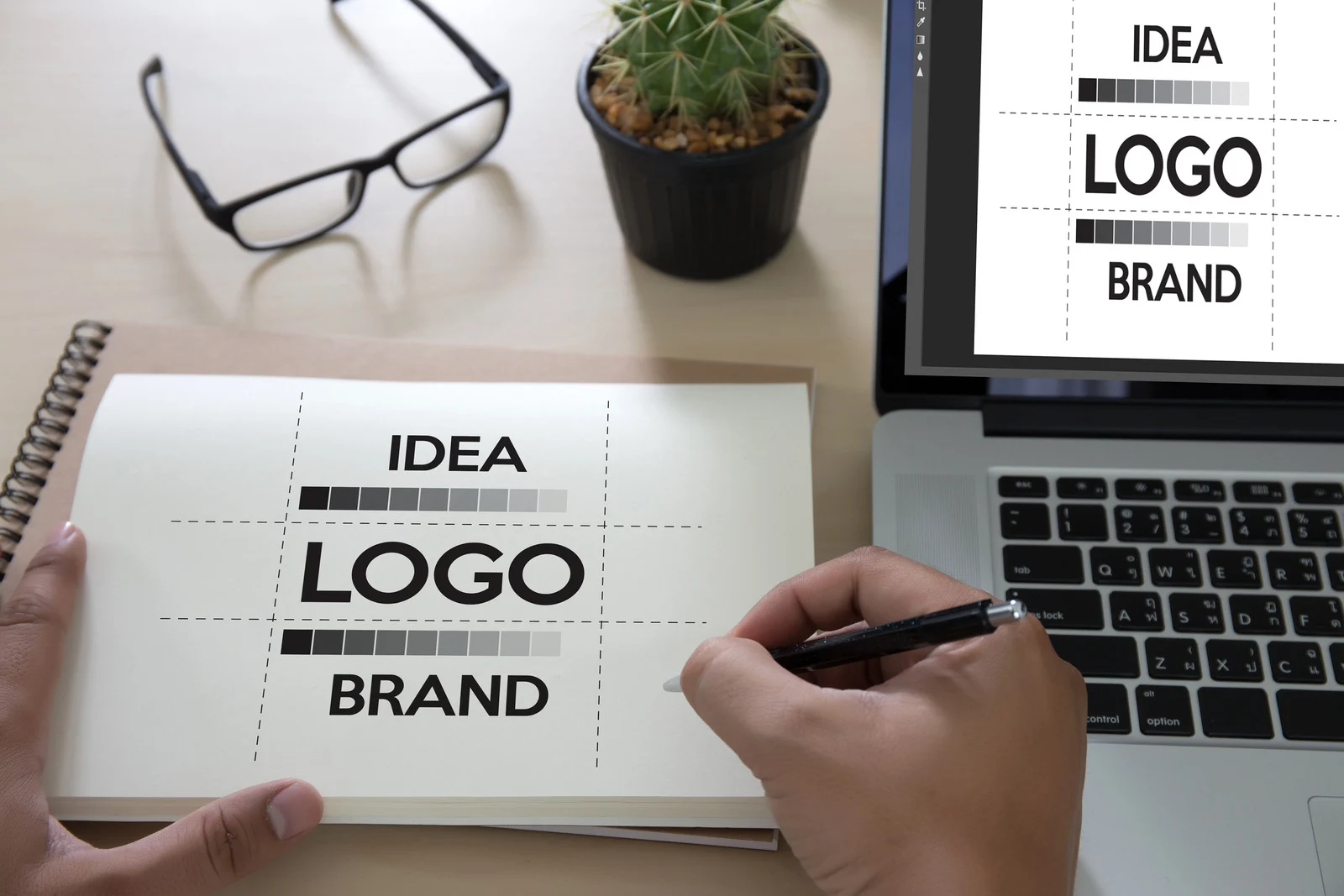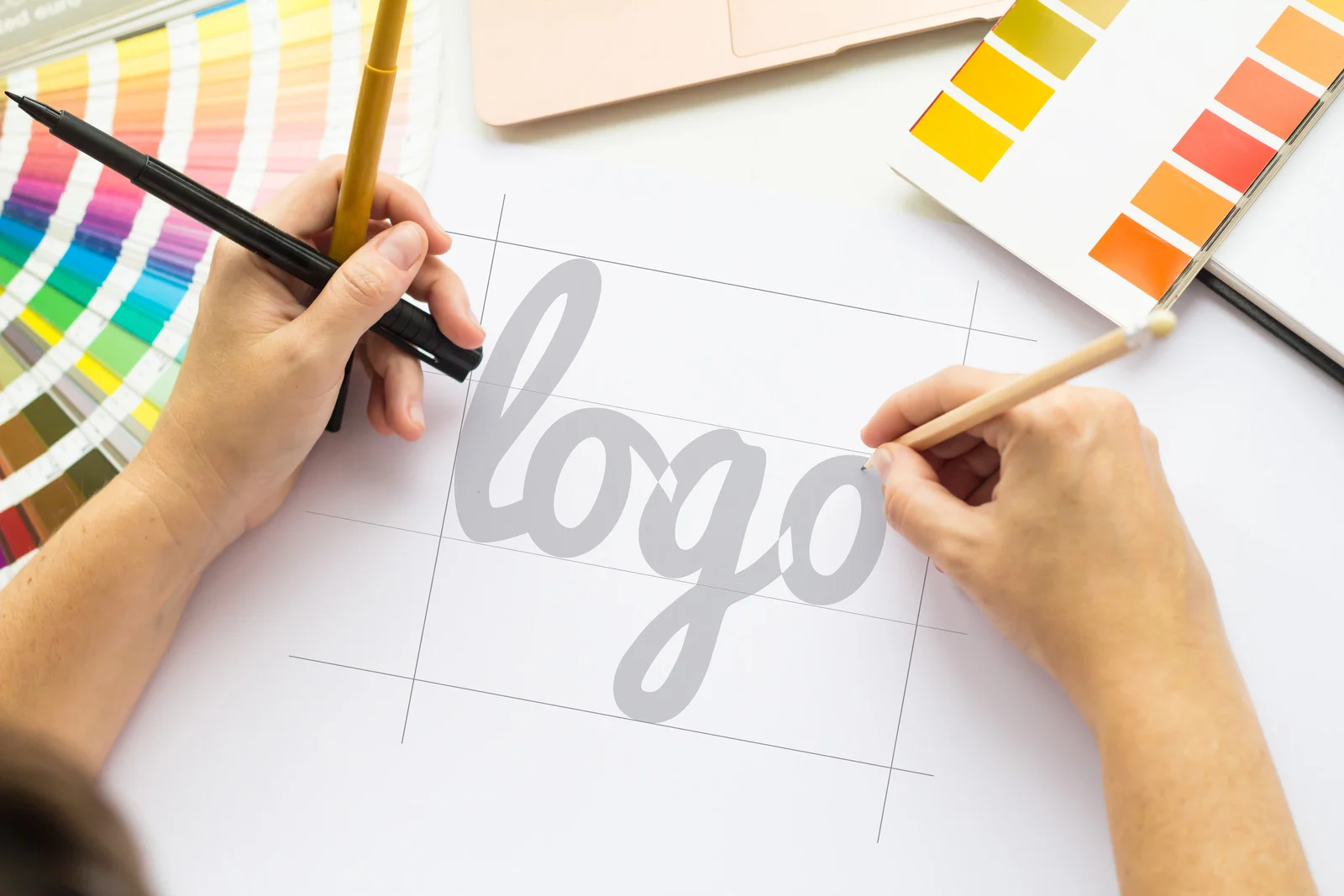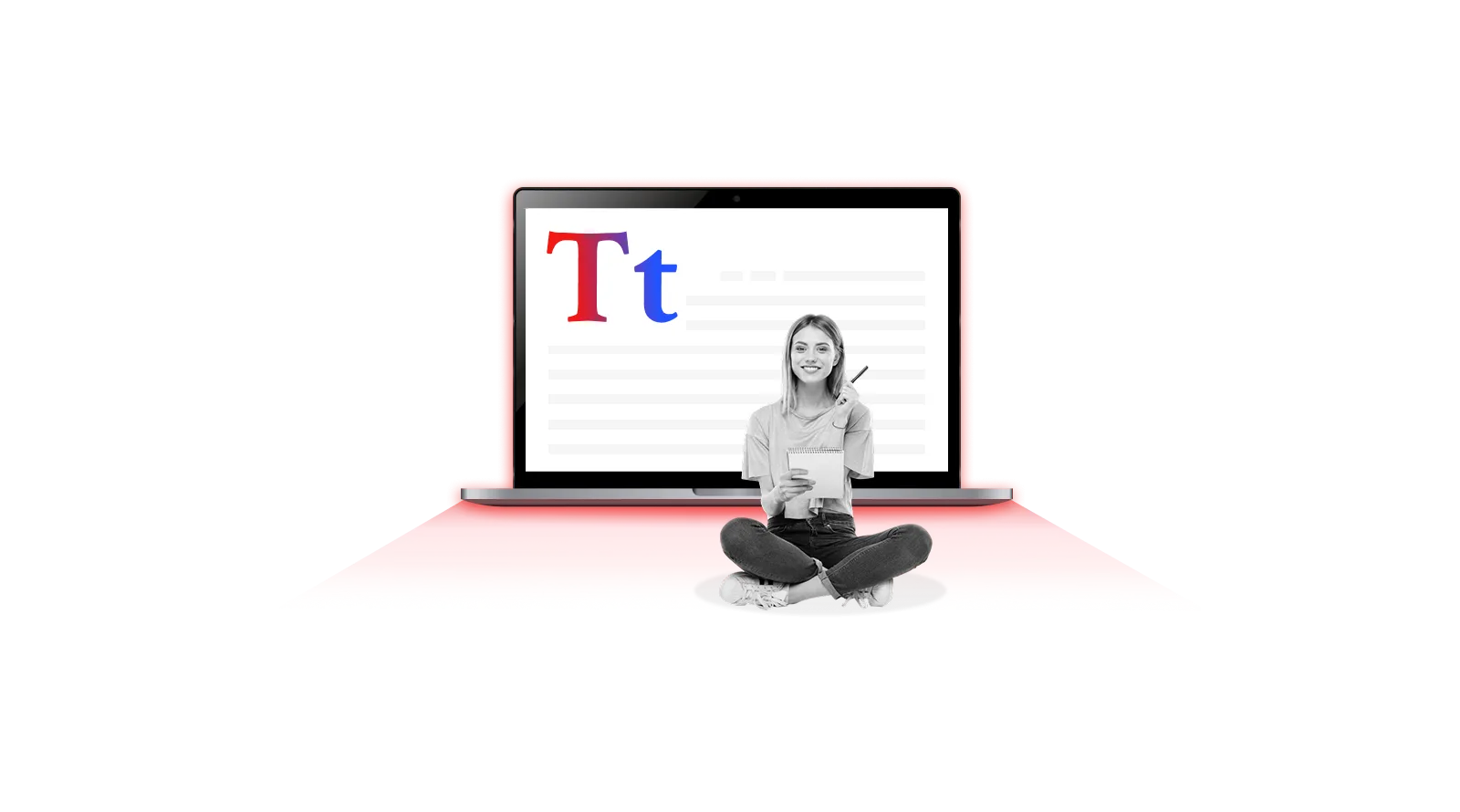
จิตวิทยาการเลือกฟอนต์ สร้าง Brand Awareness ให้ตรงใจแบรนด์และลูกค้าจดจำ
คุณเคยสงสัยไหม ทำไมเห็นโลโก้แบรนด์หรูแล้วรู้สึก “แพง” หรือเห็นป้ายร้านกาแฟบางร้านแล้วรู้สึก “อบอุ่นเป็นกันเอง” ทั้งที่ยังไม่เคยเดินเข้าไปใช้บริการ
คำตอบนั้นซ่อนอยู่ในพลังของ “ตัวอักษร” หรือ “Font” หลายคนอาจมองว่าฟอนต์เป็นเพียงเรื่องของความสวยงาม แต่ในทางการตลาดและจิตวิทยานั้น ฟอนต์ เปรียบเสมือนกับ “น้ำเสียง” ของแบรนด์ หน้าที่ของฟอนต์ คือการสื่ออารมณ์ บุคลิก และสร้างความน่าเชื่อถือ โดยไม่จำเป็นต้องเอ่ยคำพูดใด ๆ
การเลือกใช้ฟอนต์ที่ใช่จึงเป็นกุญแจสำคัญ ที่จะช่วยสร้าง Brand Awareness ให้แบรนด์ของคุณได้เข้าไปนั่งอยู่ในใจของลูกค้าตั้งแต่แรกเห็น
ทำไมความหมายของฟอนต์ ถึงมีผลต่อจิตวิทยาและ Brand Awareness?
คุณเคยไหม ที่สามารถจดจำแบรนด์ Disney หรือ Coca-Cola ได้จากการมองเห็นโลโก้เพียงแวบเดียว คุณอาจไม่เคยสังเกตว่าในโลโก้นั้นได้แฝงสิ่งที่ทรงพลังยิ่งกว่า และฝังตัวอยู่ในทุกส่วนของการสื่อสารแบรนด์นั่นก็คือ “ฟอนต์” ซึ่งมีผลโดยตรงต่อความรู้สึกและการรับรู้ของมนุษย์ ในระดับจิตวิทยา ฟอนต์ ไม่ใช่แค่ภาพลักษณ์ แต่ยังเป็นตัวกระตุ้นอารมณ์และความจำ ที่มีผลต่อการตัดสินใจของผู้บริโภคอย่างคาดไม่ถึง
การเลือกใช้ ฟอนต์ จึงส่งผลโดยตรงต่อ Brand Awareness ผ่านกระบวนการทางจิตวิทยาดังนี้
สมองจดจำ “รูปทรง” ก่อน “ความหมาย”
ก่อนที่เราจะอ่านออกว่าข้อความเขียนว่าอะไร สมองจะบันทึก “รูปร่างของตัวอักษร” (Visual Shape) ไปก่อนแล้ว หากคุณใช้ฟอนต์ที่มีเอกลักษณ์และสม่ำเสมอ สมองลูกค้าจะจดจำ “Pattern” นั้น และเชื่อมโยงกลับมาที่แบรนด์ของคุณทันที โดยที่ลูกค้าไม่ต้องย้อนกลับไปดูชื่อแบรนด์อีกครั้ง
สร้าง “อารมณ์ร่วม” ระดับจิตใต้สำนึกผ่านรูปทรง
Font แต่ละแบบมี “บุคลิก” ที่กระตุ้นความรู้สึกของมนุษย์ได้ต่างกัน เช่น
- เส้นโค้งมน : สื่อถึงความสุข ความเป็นมิตร (เช่น โลโก้ Disney)
- เส้นเหลี่ยมหนา : สื่อถึงความมั่นคง พลังอำนาจ (เช่น โลโก้ธนาคาร)
เมื่อลูกค้าเห็นฟอนต์ที่ตรงกับจริตของพวกเขา จะเกิดความรู้สึก “ไว้ใจ” และ “คุ้นเคย” ซึ่งเป็นรากฐานสำคัญของการตัดสินใจซื้อ
สร้างความแตกต่าง (Differentiation) ในเสี้ยววินาที
ในตลาดที่มีคู่แข่งมากมาย Typography (ศิลปะการจัดวางตัวอักษร) คือเครื่องมือที่ช่วยแยกแยะแบรนด์ของคุณออกจากคู่แข่งได้ชัดเจนที่สุด เพื่อให้ลูกค้าสามารถจดจำและแยกแยะแบรนด์ของเราได้ทันที เพียงแค่กวาดตามองในเสี้ยววินาที
4 กลุ่มฟอนต์ยอดนิยมและความลับที่ซ่อนอยู่ในลายเส้น
ในโลกการออกแบบแบรนด์ ฟอนต์ไม่ได้ต่างกันแค่ “รูปทรง” แต่ยังคงซ่อนความหมายทางจิตวิทยาที่สามารถเปลี่ยนภาพลักษณ์ของแบรนด์ได้อย่างคาดไม่ถึง
โดยทั่วไป ฟอนต์ถูกแบ่งออกเป็น 4 กลุ่มหลักยอดนิยม ได้แก่
Serif (ฟอนต์แบบมีเชิง)
เป็นฟอนต์ที่มีความทางการ ให้ความรู้สึกน่าเชื่อถือ, น่าเคารพ, หรูหรา โดยมีจุดเด่นคือ มี “เชิง ” หรือส่วนปลายเล็กๆยื่นออกมาจากตัวอักษร ทำให้อ่านง่ายและให้ความรู้สึกมั่นคง
เหมาะกับธุรกิจ : กฎหมาย, การเงิน, สถาบันการศึกษา, และแบรนด์แฟชั่น Hi-End
ตัวอย่างแบรนด์ที่ใช้ฟอนต์แบบ Serif : Rolex, Vogue, Dior
Sans Serif (ฟอนต์แบบไม่มีเชิง)
เป็นฟอนต์ที่ให้ความรู้สึกเรียบง่าย, ทันสมัย, เข้าถึงง่าย โดยมีจุดเด่นคือไม่มี “เชิง” ไม่มีส่วนตกแต่งมีเพียงลายเส้นตัวอักษรเรียบๆ
เหมาะกับธุรกิจ : Tech Startup, เว็บไซต์ E-Commerce, แอปพลิเคชัน, และแบรนด์ไลฟ์สไตล์คนรุ่นใหม่
ตัวอย่างแบรนด์ที่ใช้ฟอนต์แบบ Sans Serif : Facebook, Airbnb, Microsoft
Script (ฟอนต์ลายมือ/ตัวเขียน)
เป็นฟอนต์ที่เน้นความพริ้วไหว สื่อถึง “อารมณ์” ให้ความรู้สึก สง่างาม, โรแมนติก, สนุกสนานขี้เล่น จุดเด่นคือการเลียนแบบลายมือการเขียนด้วยปากกาหรือพู่กัน
เหมาะกับธุรกิจ : อาหารและเครื่องดื่ม, ความสวยความงาม, งานแต่งงาน, และสินค้าสำหรับเด็ก
ตัวอย่างแบรนด์ที่ใช้ฟอนต์แบบ Script : Coca-Cola, Cartier, Champion
Display/Modern (ฟอนต์พาดหัว/เฉพาะทาง)
เป็นฟอนต์ที่ถูกออกแบบมาเพื่อ “โชว์” หรือ “ดึงดูดสายตา” มักมีรูปทรงโดดเด่น แปลกตา สร้างความประทับใจตั้งแต่แรกเห็น
เหมาะกับธุรกิจ : โลโก้สินค้า, โปสเตอร์ภาพยนตร์, ธุรกิจบันเทิง, หรือแคมเปญโฆษณาที่ต้องการความโดดเด่น
ตัวอย่างแบรนด์ที่ใช้ฟอนต์แบบ Display : Disney, LEGO, Fanta
4 ขั้นตอนเลือก Font ให้ตรงใจแบรนด์ (Brand Personality Matching)
การเลือกฟอนต์ไม่ได้เป็นเพียงเรื่องของความสวยงาม แต่ฟอนต์คือ “น้ำเสียง” ที่แบรนด์ใช้สื่อสารกับลูกค้า ฟอนต์แต่ละแบบมีจิตวิทยาที่ซ่อนอยู่ต่างกัน การเลือกฟอนต์ที่ไม่เหมาะสมกับประเภทธุรกิจอาจเป็นการทำลายความน่าเชื่อถือของแบรนด์ แต่หากเลือกถูกต้อง ก็จะช่วยส่งเสริม Brand Awareness ให้ลูกค้าจดจำแบรนด์ของคุณได้ตั้งแต่แรกเห็น
โดย 4 ขั้นตอนการเลือก Font ให้ตรงใจแบรนด์ มีแนวทางดังนี้
กำหนดบุคลิกแบรนด์ให้ชัด (Brand Persona)
การกำหนดบุคลิกให้ชัดเจนเป็นการตอบคำถามว่า “แบรนด์ของคุณจะเป็นคนแบบไหน?” ก่อนที่จะเลือกฟอนต์ให้ลองลิสต์คำคุณศัพท์ (Adjective) 3-5 คำ ที่บ่งบอกตัวตนแบรนด์ของคุณได้ชัดเจนที่สุด เพราะคำเหล่านี้จะนำพาคุณให้เลือกฟอนต์ได้ถูกต้องตาม Brand Persona (บุคลิกภาพของแบรนด์)
ถ้าแบรนด์คุณคือความน่าเชื่อถือ, มั่นคง, หรูหรา : เลือกใช้ฟอนต์กลุ่ม Serif
ถ้าแบรนด์คุณคือความทันสมัย, เป็นกันเอง, เข้าถึงง่าย : เลือกใช้ฟอนต์กลุ่ม Sans Serif
ถ้าแบรนด์คุณคือความคิดสร้างสรรค์, อ่อนโยน, งานฝีมือ : เลือกใช้ฟอนต์กลุ่ม Script
ถ้าแบรนด์คุณคือความโดดเด่น, มีเอกลักษณ์, แปลกตา : เลือกใช้ฟอนต์กลุ่ม Display
เน้นความอ่านง่าย (Readability is King)
กฎเหล็กของการออกแบบเพื่อการสื่อสารคือ “ถ้าอ่านไม่ออก ก็ไม่มีความหมาย”
ดังนั้นการเลือกฟอนต์ จึงต้องมากกว่าความสวยงาม แต่ยังต้องสามารถสื่อความหมายถึงลูกค้าได้ เพราะถ้าหากลูกค้าต้องใช้ความพยายามในการแกะตัวอักษร พวกเขาอาจจะเลื่อนผ่านได้ทันที
สิ่งที่ควรพิจารณา :
- ระยะห่างตัวอักษร (Tracking/Letter-spacing)
- ขนาดฟอนต์ที่เหมาะสมในแต่ละแพลตฟอร์ม
- ความชัดของเส้น (Stroke)
- ความคมชัดทั้งบน Desktop / Mobile
ตัวอย่างเช่น :
- ฟอนต์ Script อาจสวยและมีเสน่ห์ แต่ถ้าใช้ในหัวข้อยาวๆ อาจทำให้อ่านลำบาก
- ฟอนต์ Display ใช้ได้ดีสำหรับ Headline แต่ไม่เหมาะกับเนื้อหาหลัก
จำกัดจำนวน Font (Consistency)
การเลือกฟอนต์ควรใช้ไม่เกิน 3 แบบ เพราะหากใช้ฟอนต์หลายแบบอาจทำให้ลูกค้าต้องประมวลผลเพิ่มขึ้น ส่งผลให้สามารถจดจำแบรนด์ได้ยากขึ้น ความสม่ำเสมอในการเลือกใช้ฟอนต์จึงจะทำให้ลูกค้าสามารถเชื่อมโยงภาพลักษณ์แบรนด์ได้ทันที แม้จะยังไม่เห็นโลโก้ก็ตาม เพราะฟอนต์คือส่วนหนึ่งของ “Brand Identity”
โดยมีการจำกัดจำนวนฟอนต์ดังนี้ :
Primary Font : ฟอนต์หลักสำหรับพาดหัว (เน้นเอกลักษณ์แบรนด์)
Secondary Font : ฟอนต์รองสำหรับเนื้อหา (เน้นอ่านง่าย)
Accent Font (ถ้ามี) : ฟอนต์สำหรับคำโปรยสั้นๆ หรือ Call to Action (เน้นความแตกต่าง)
ทดสอบกับบริบทจริง (Context Testing)
ฟอนต์ที่ดูสวยบนหน้าจอคอมพิวเตอร์ อาจไม่เหมาะกับการอยู่บนหน้าจอมือถือ หรือฉลากสินค้าขนาดเล็ก ดังนั้นขั้นตอนสุดท้ายก่อนการตัดสินใจเลือกใช้ฟอนต์ คือการทำ Context Testing หรือการทดสอบในสภาพแวดล้อมการใช้งานจริง โดยมีขั้นตอนดังนี้
Scale Test : ลองย่อฟอนต์ให้เล็กสุดๆ แล้วยังอ่านรู้เรื่องหรือไม่?
Color Test : เมื่อเปลี่ยนเป็นสีขาว-ดำ หรือวางบนพื้นหลังที่ยุ่งเหยิง ตัวอักษรยังจมหรือไม่?
Platform Test : ตรวจสอบการแสดงผลบน Browser ต่างๆ และ Mobile Devices ว่าฟอนต์มีการแสดงผลผิดเพี้ยนหรือไม่ (โดยเฉพาะฟอนต์ภาษาไทยอาจเกิดปัญหาเรื่องสระลอย)
สรุป
การเลือกฟอนต์ จึงไม่ใช่แค่เรื่องของ ‘ความสวยงาม’ แต่คือเครื่องมือสื่อสารระดับจิตวิทยาที่ช่วยให้ลูกค้าจดจำแบรนด์ของคุณได้ง่ายขึ้น ทั้งในด้านอารมณ์ ความรู้สึก ความน่าเชื่อถือ และการสร้างเอกลักษณ์ที่แตกต่าง
หากคุณเลือกใช้ฟอนต์ได้เหมาะสมและสอดคล้องกับบุคลิกของแบรนด์ ฟอนต์จะทำหน้าที่เป็นเสมือน ‘น้ำเสียง’ ที่คอยสื่อสารกับลูกค้าโดยที่คุณไม่ต้องเปล่งคำใดๆ